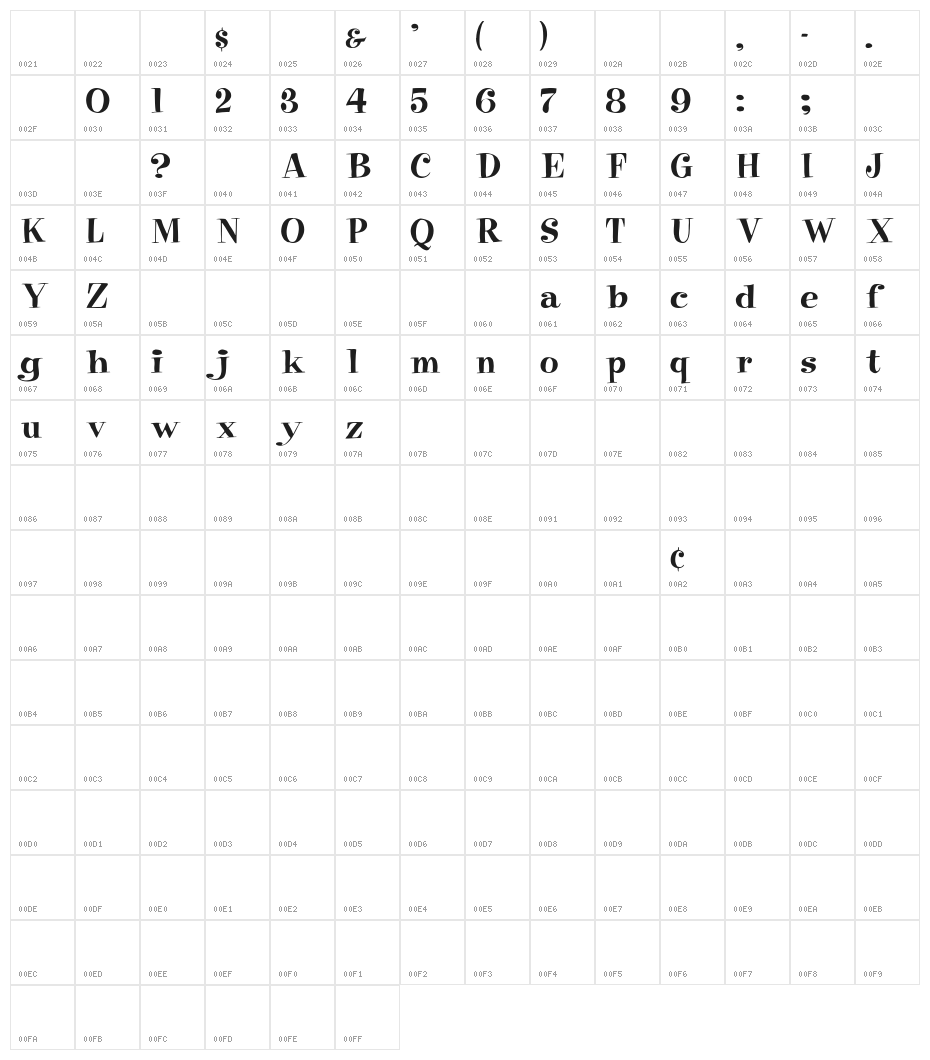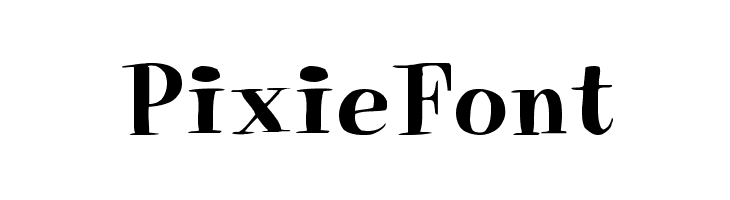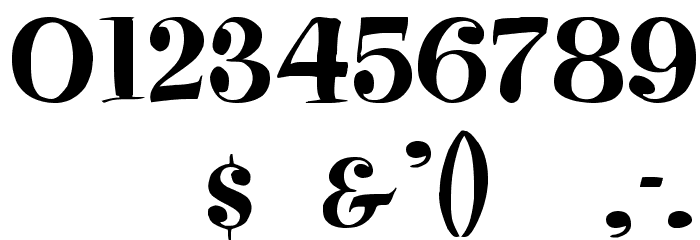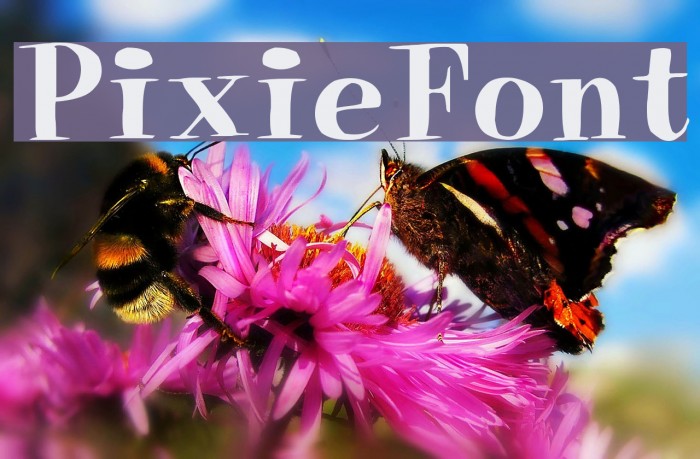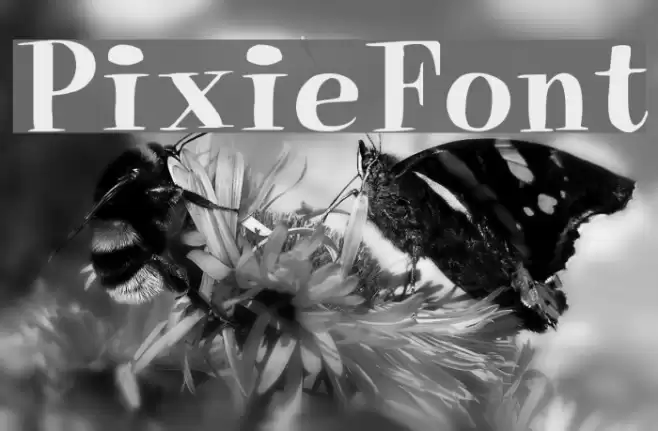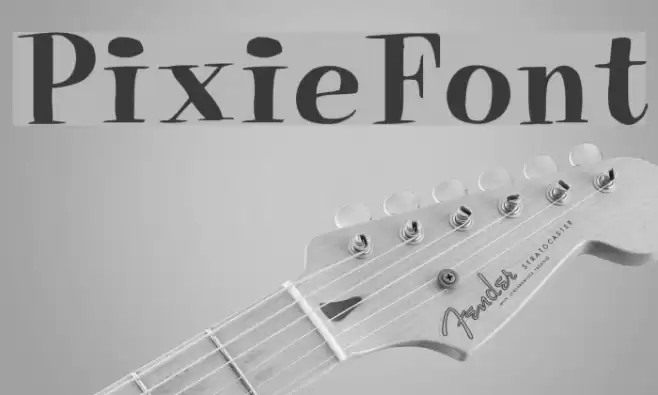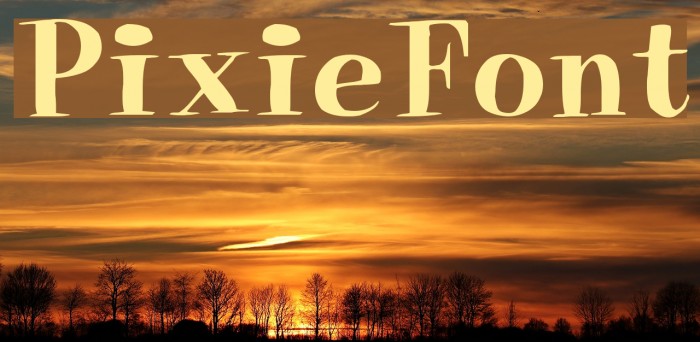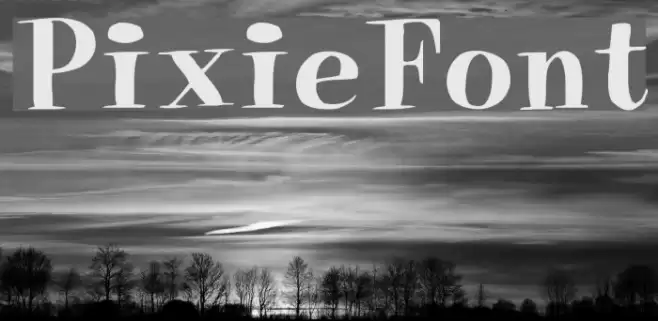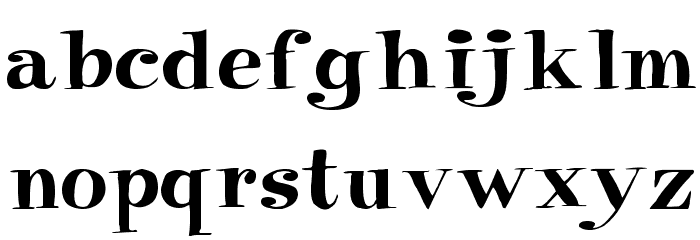
PixieFont Font
✎ Serif
Fonts by David Rakowski
| カテゴリ | Serif |
| 全体的なスタイル | Playful and Whimsical |
| おすすめプロジェクト | Ideal for children's books, playful branding, creative posters, and whimsical invitations. |
| 作者 | Fonts by David Rakowski |